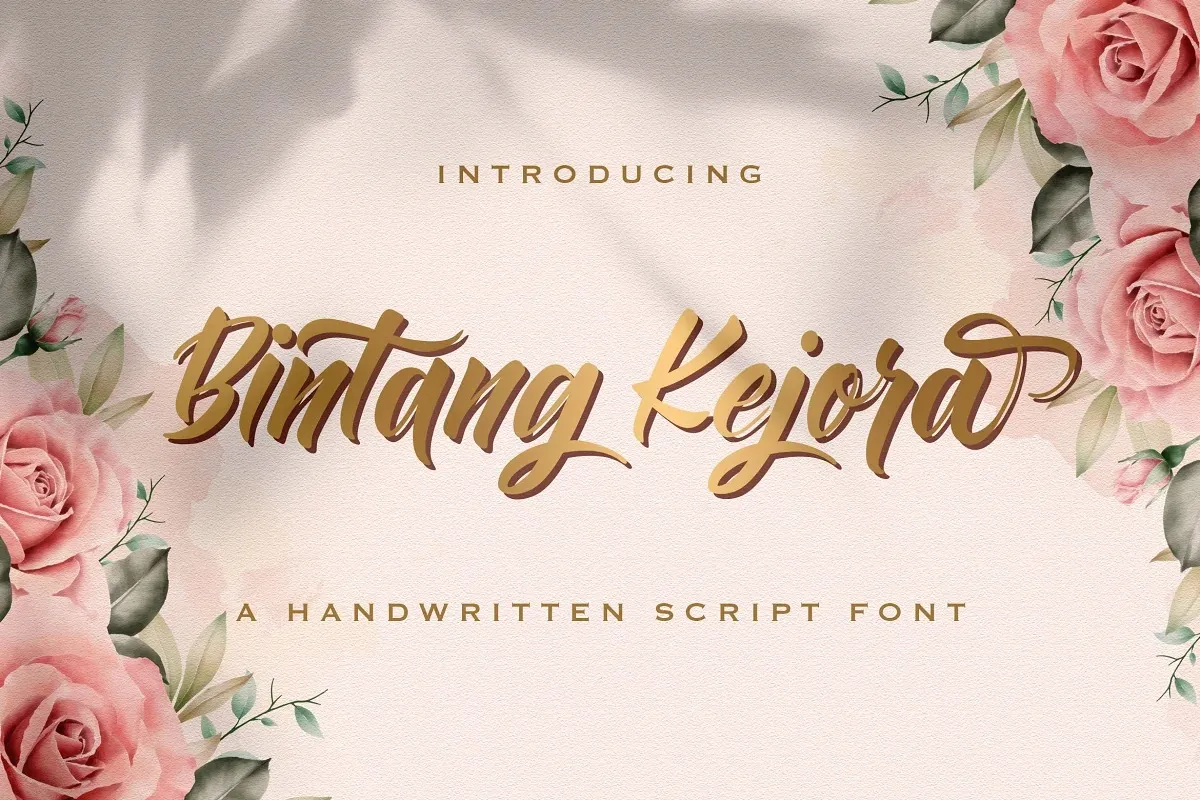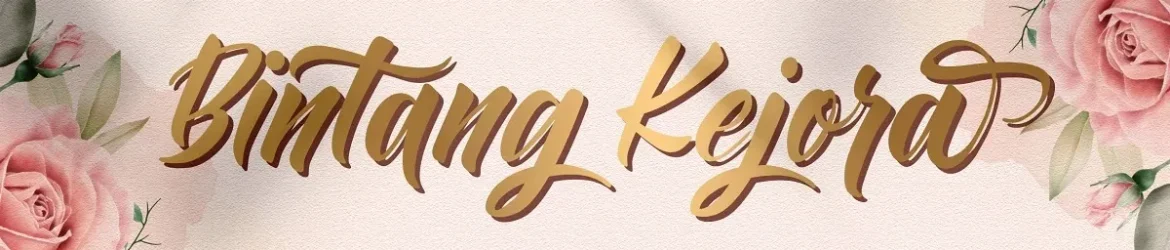
A Bintang Kejora é uma fonte script que combina elegância vintage com criatividade incansável. Ela foi criada pelo designer StringLabs e carrega consigo um equilíbrio de caracteres impressionante, fazendo-a perfeitamente adaptável a uma ampla variedade de projetos. Este atributo faz dela uma escolha inteligente para quem deseja dar vida a suas mais inovadoras ideias gráficas, adquirindo um toque vintage e sofisticado que vai marcar sua marca. Descubra o brilho natural desta fonte em designs variados.